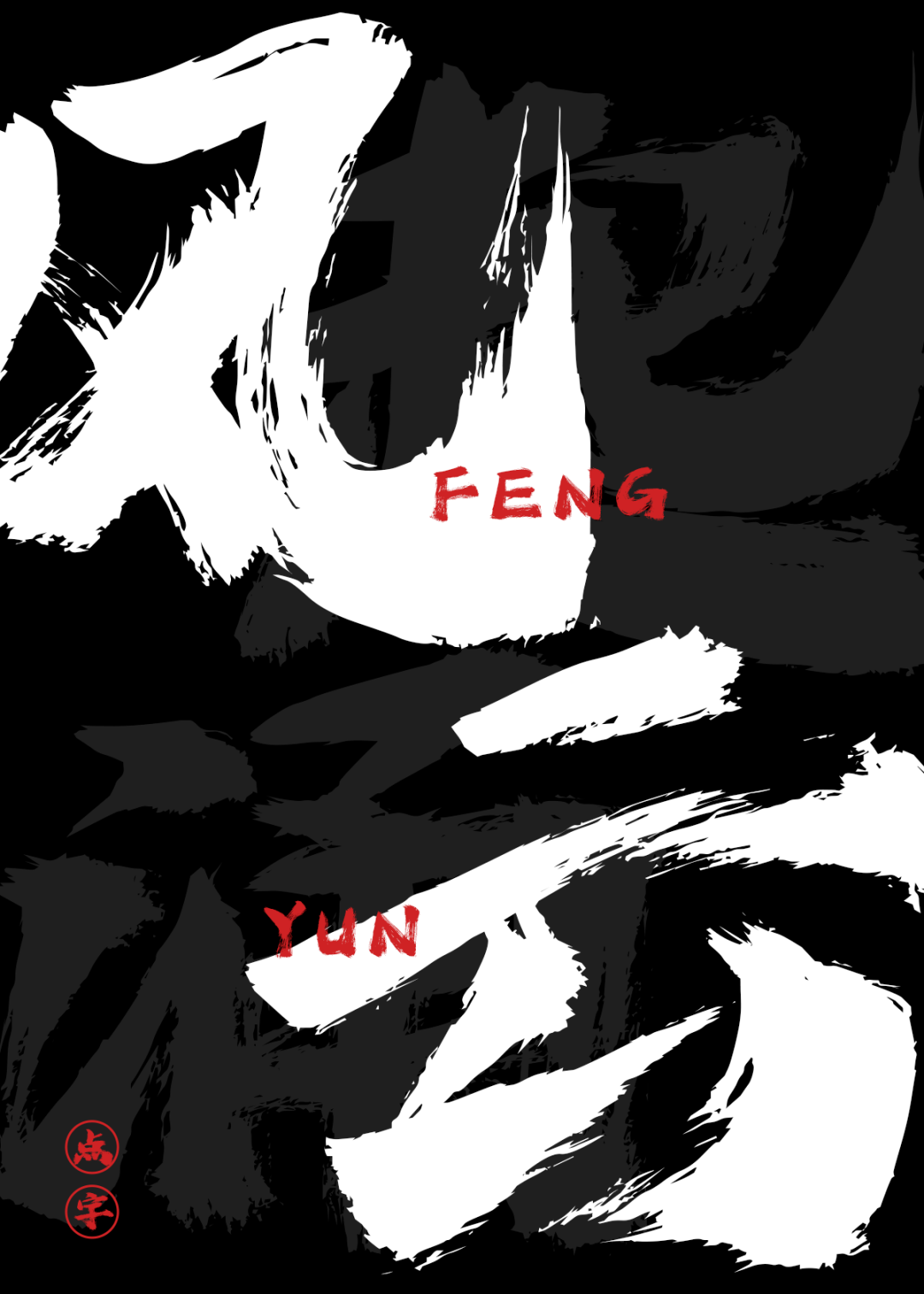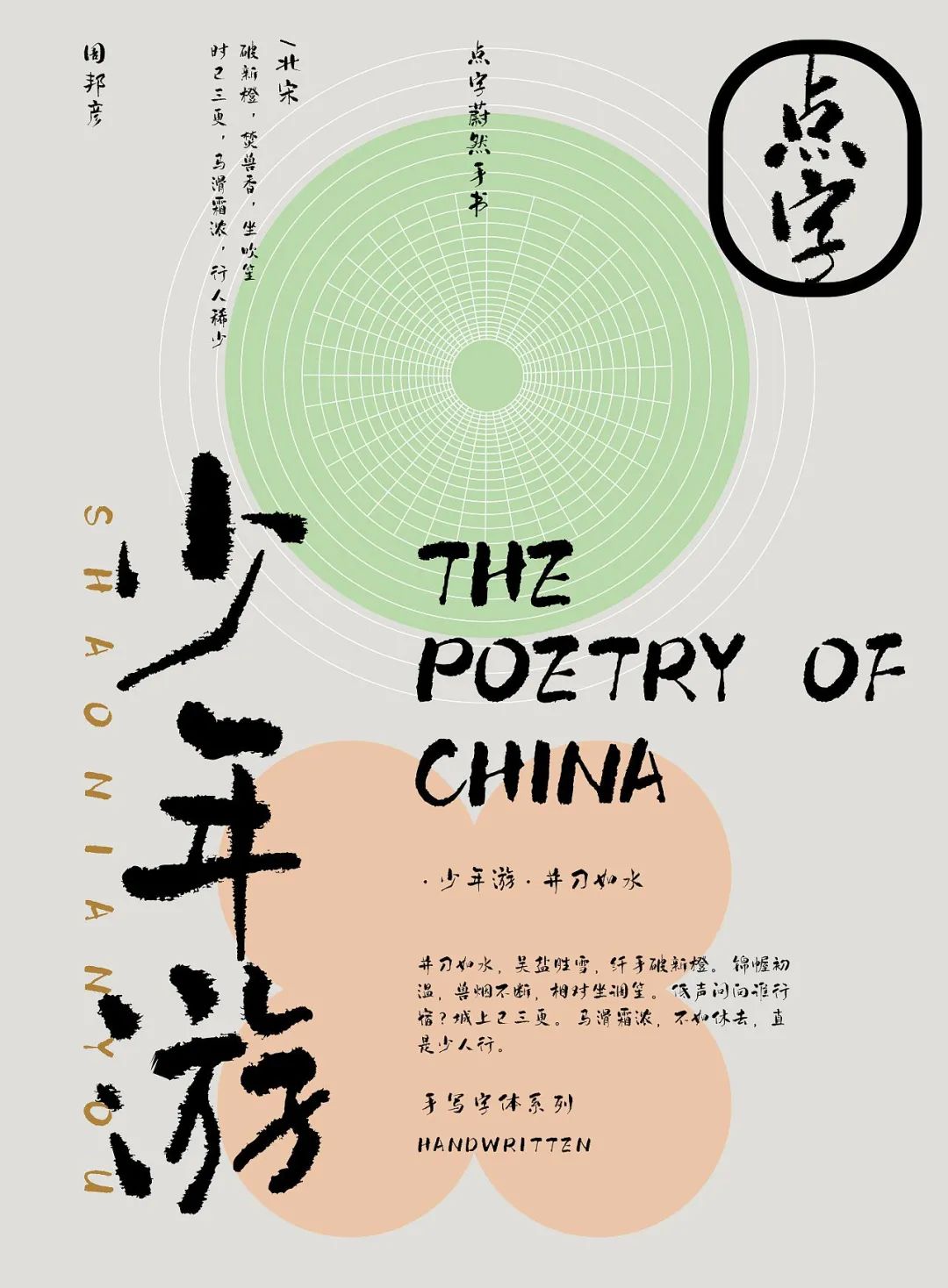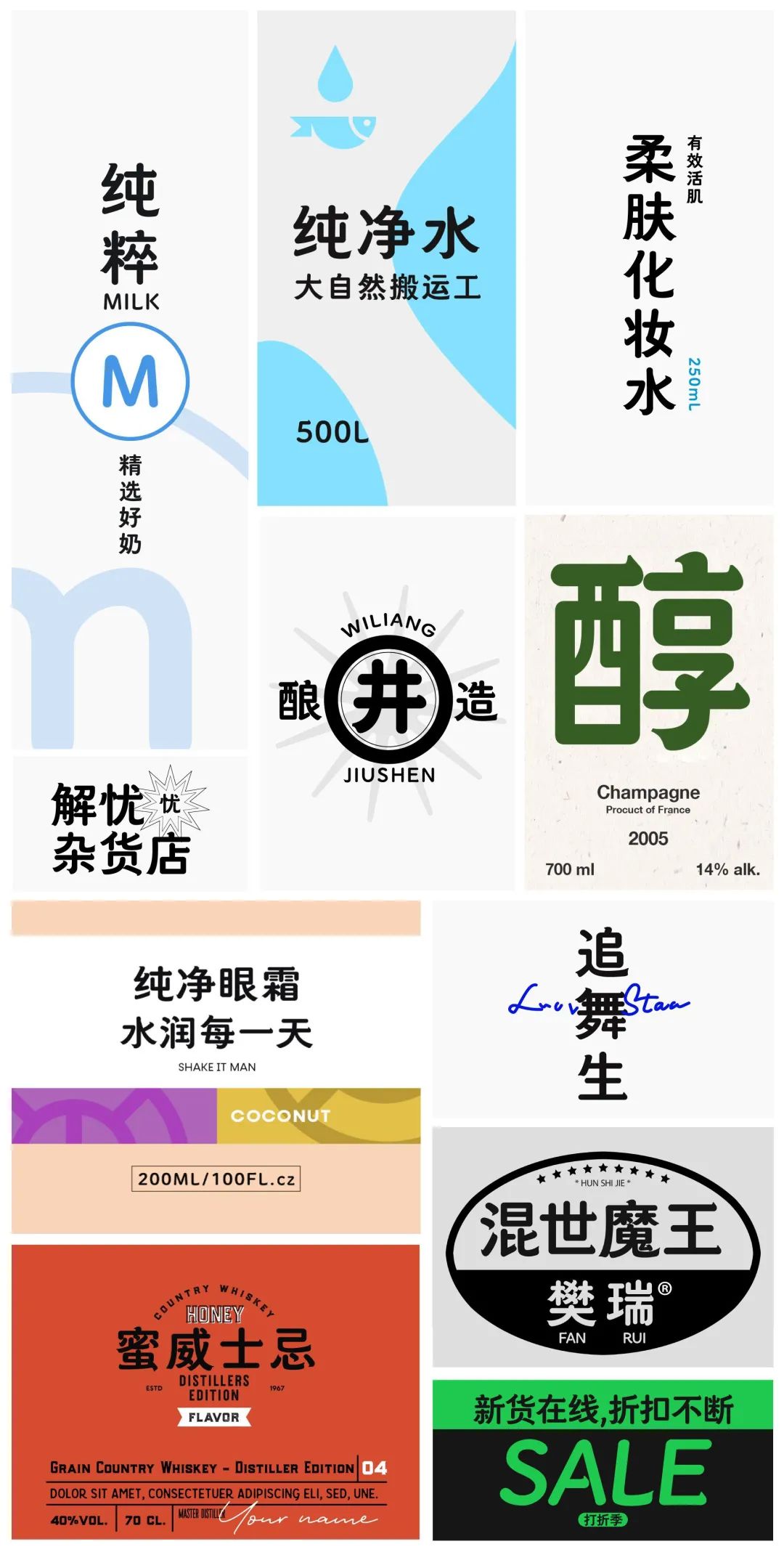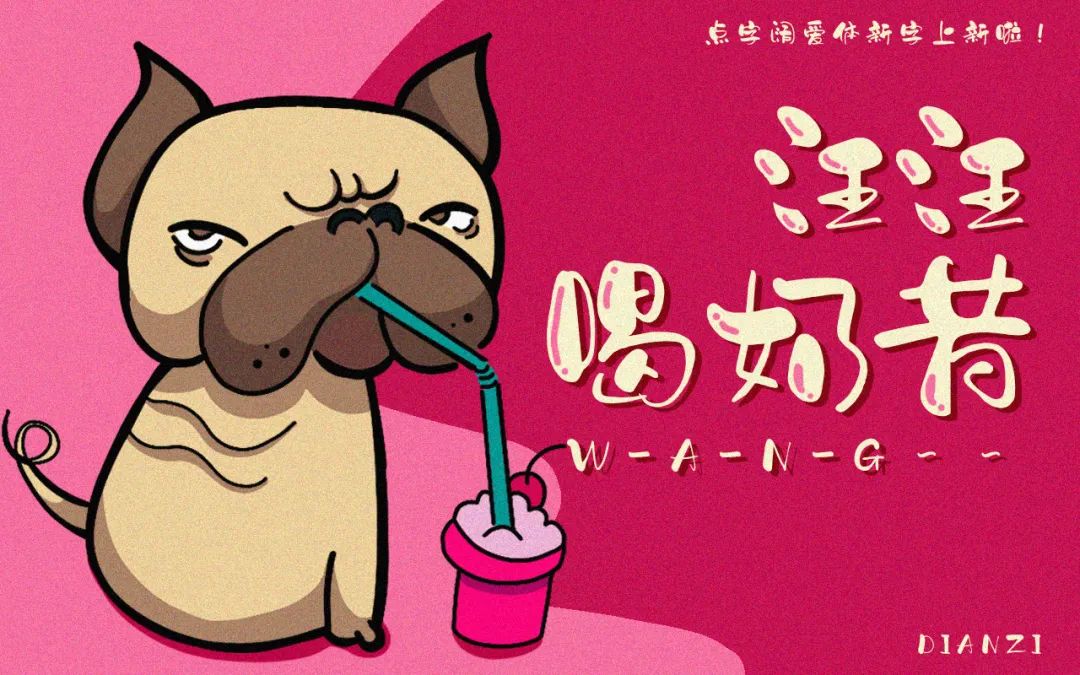
设计师放心商用的字体分享,拿来吧你!
你以为我今天又要发免费字?emmm,是,也不完全是……因为字由上免费商用的字体,已经有890款了,足够你真香了!但即使这么多数量的字体,还是有人抱怨不够,原因就是可用的太少,你既需要不费脑的“百搭”字体,也需要分场合的“定制”字体。柚子细数了一下(以中文为例),只有8款能满足百搭(字由出品的就占了3款)。而剩下的25款能满足定制(毕竟免费的,要啥自行车),不过你还有两条路,要么就是才华横溢,自己设计字体,要么就是买字体版权,第一条路有门槛,还耗精力,第二条路没门槛,但耗钱……别蓝瘦,这不是全宇宙最阔爱最贴心的柚子带着字由会员来了吗!一个月省下38元的奶茶钱,就可以商用195款会员字体,平均一款字体不到2毛钱,就算是刚入门的设计小白,也毫无压力吧!而且会员到期前你设计的作品,注册的logo都可以终身商用,完全不用担心不续费就侵权,定心丸给你吃得死死的。看起来字由会员既便宜又安全,那字体产品会不会注水啊?不仅不注水,还加量不加价,比如最近新上了好几款:
你想要的霸气的、清新的、复古的、可爱的、古典的、百搭的 ,这里都有,做设计再也不用巧妇难为无米之炊了~